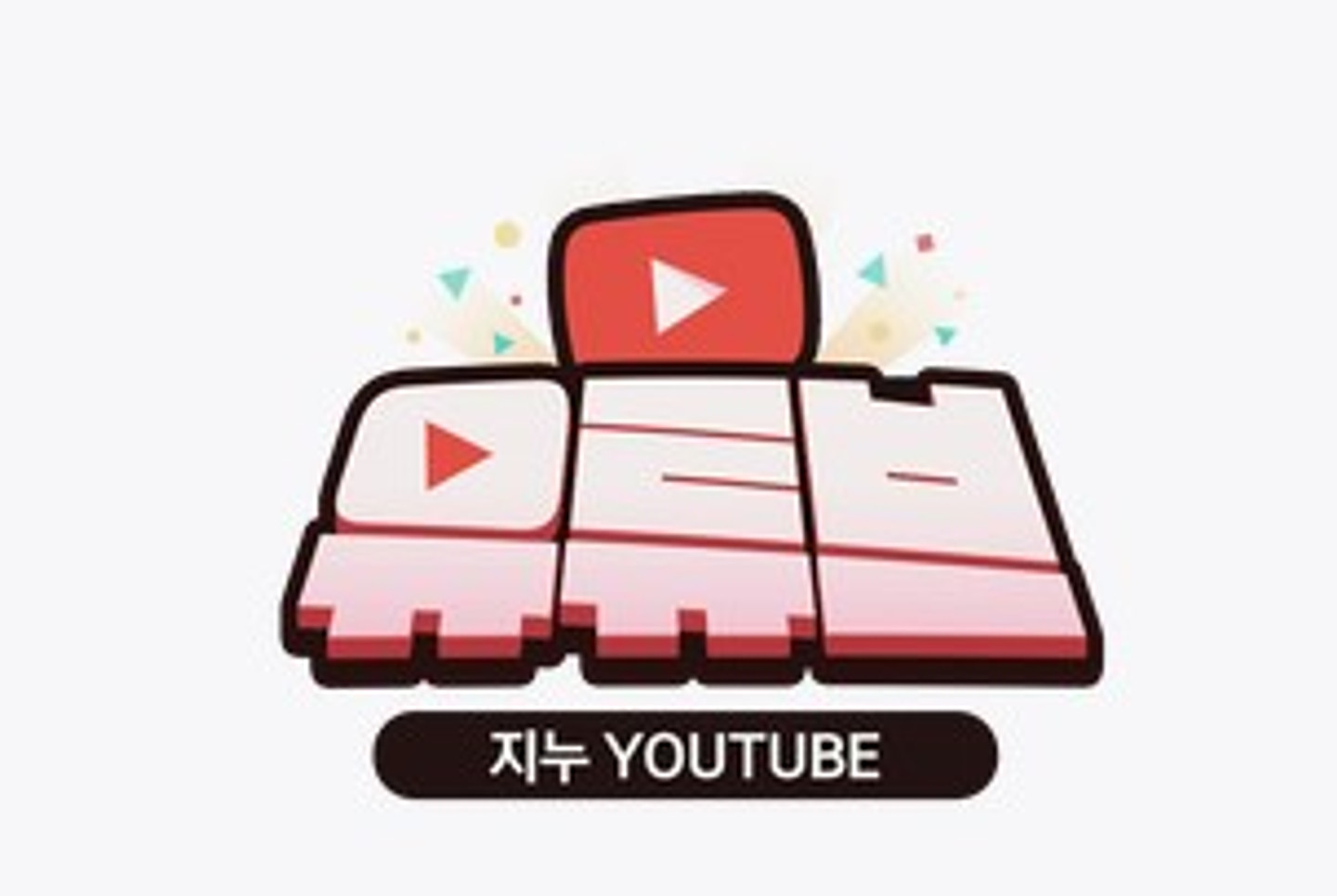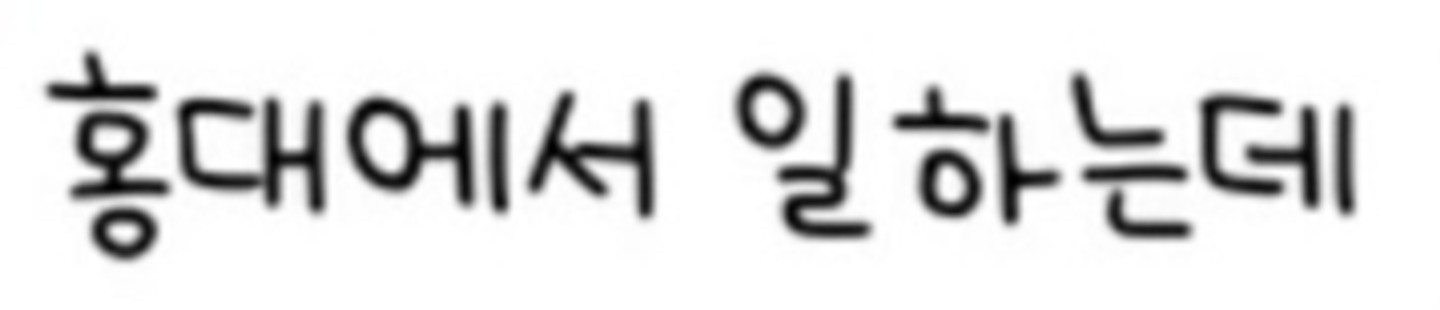
트위치 방송하시는분 프로필에 있는 건데 저기 유튜브는 무슨 폰트를 베이스로 만든걸까요? 혹시 비슷하기라도 한 폰트 있을 까요?
이거 무슨 폰트인가요ㅠ
무슨 폰트일까요?!!ㅠㅠㅠ손글씨처럼 예쁘고 가독성 졓아서 찾고싶습니더....🥹
혹시 이 폰트 뭔지 알 수 있을까요...?!!!?
핑크색으로 되어있는 부분 폰트 어떤걸까요?!
이거 무슨 폰트인지 알 수 있을까요????
Never just drive. 폰트 궁금해요
총 3가구 전체 매매 ~ 건물 전체 관리의 어려움 글씨체 뭘까요...? ㅠㅠ 구해줘 홈즈에 나오는 폰트예요 ㅠㅠ!
무슨 폰트인지 알려주세요ㅠㅠ
폰트 영원히 찾고 있어요.............